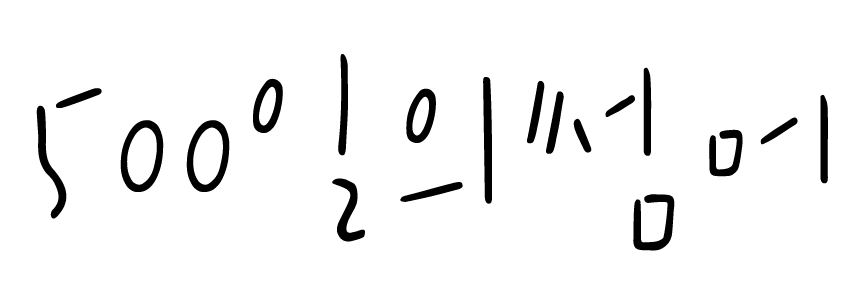
TSC500일썸머
서정적제목용
‘TSC 500일의썸머’는 감성적인 분위기를 담고 있는 손글씨 폰트다. 폰트의 이름처럼 시원하고 담백한 획으로 이루어져 크기감이 다양한 손글씨 폰트지만 차분한 인상을 준다. Regular와 Bold는 같은 구조를 가지지만 획의 질감을 달리해 각각 개성을 가지도록 했다.
• 양예슬 최미진
• TSC500일썸머 / TSC500daysofsummer